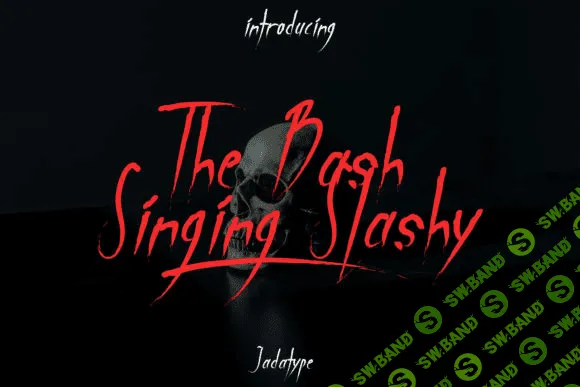
Название: The Bash Singing Slashy Font
Bash Singing Slashy - это шрифт с ужасающим видом.
Он может быть добавлен в различные дизайны, связанные с вечеринками или творениями Хэллоуина.